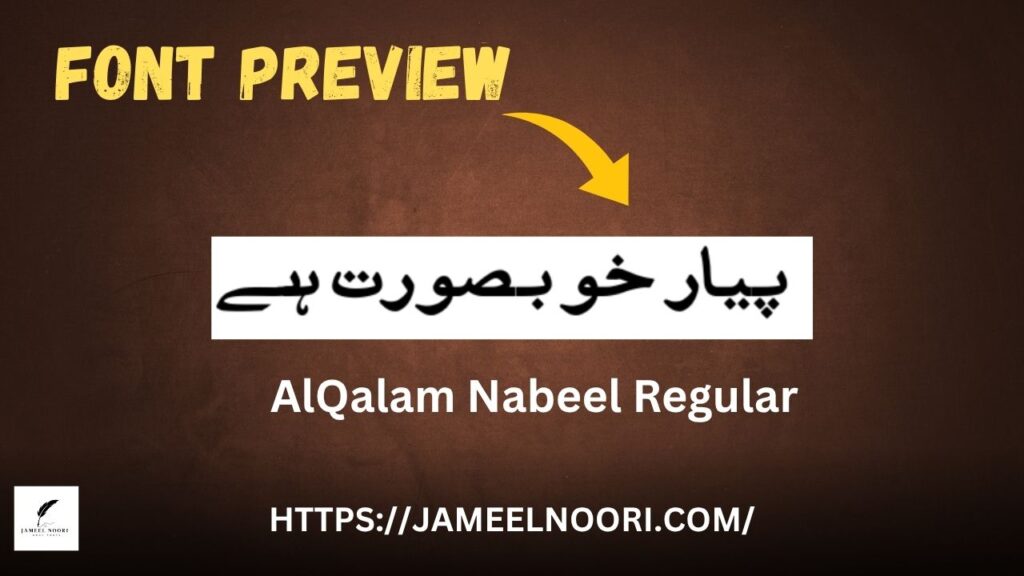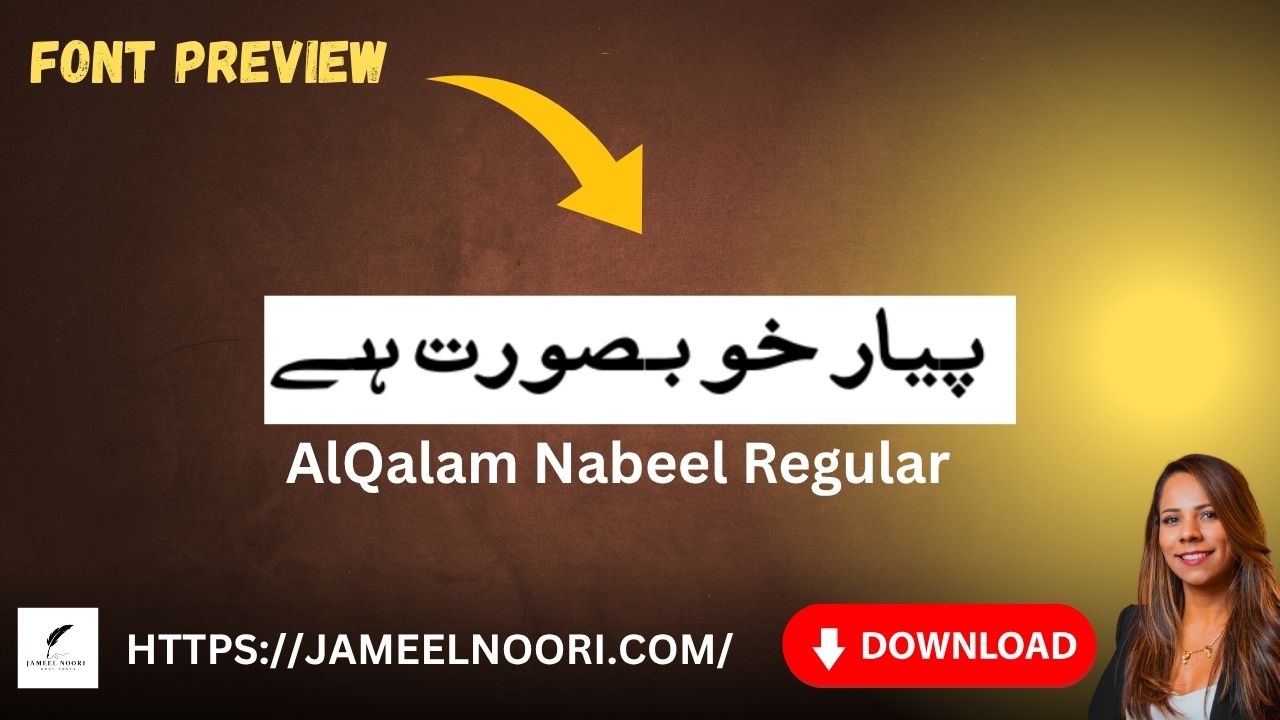
Urdu Font AlQalam Nabeel aik bohot hi popular aur stylish Urdu font hai jo designers aur writers dono ke liye perfect hai. Yeh font TrueType Font (TTF) format me available hai aur iska use web designing, logo creation aur Urdu typing ke liye hota hai. Iska style simple aur readable hai, jo Urdu likhne walon ke liye bohot asaan aur attractive banta hai.
Features of Urdu Font AlQalam Nabeel
- Perfect for Urdu typing aur calligraphy
Why Choose Urdu Font AlQalam Nabeel?
- Yeh font professional look deta hai.
- Graphic designers aur content creators ke liye best choice hai.
- Printing aur digital use dono me clear readability deta hai.
- AlQalam Nabeel font Urdu content ko premium aur elegant touch deta hai.
Uses of AlQalam Nabeel Urdu Font in Pakistan
Urdu Font AlQalam Nabeel Pakistan me kai fields me use hota hai, jaise:
- Urdu newspapers aur books ke layout me.
- Logo design aur poster creation me.
- YouTube thumbnails aur social media posts ke liye.
- Urdu typing aur Microsoft Word documents ke liye.
Tips for Using AlQalam Nabeel Urdu Font Professionally
- Font size 14–18 points ke beech rakhein readability ke liye.
- Headlines ke liye bold version use karein.
- Design software (Photoshop, CorelDRAW) me high-resolution output prefer karein.
Urdu Font AlQalam Nabeel aik perfect Urdu font hai jo readability, style aur professionalism ka best combination hai. Pakistan ke log is font ko design aur Urdu writing dono ke liye pasand karte hain. Agar aap ek creative designer hain to yeh font aapke toolkit ka must-have part hona chahiye.
What is Urdu Font AlQalam Nabeel used for?
It’s mainly used for Urdu writing, design, and digital content creation.
Is it suitable for Urdu calligraphy?
Yes, it gives an elegant and stylish look for Urdu calligraphy.
Can I use it for YouTube thumbnails?
Absolutely! It’s great for thumbnails, banners, and posts.